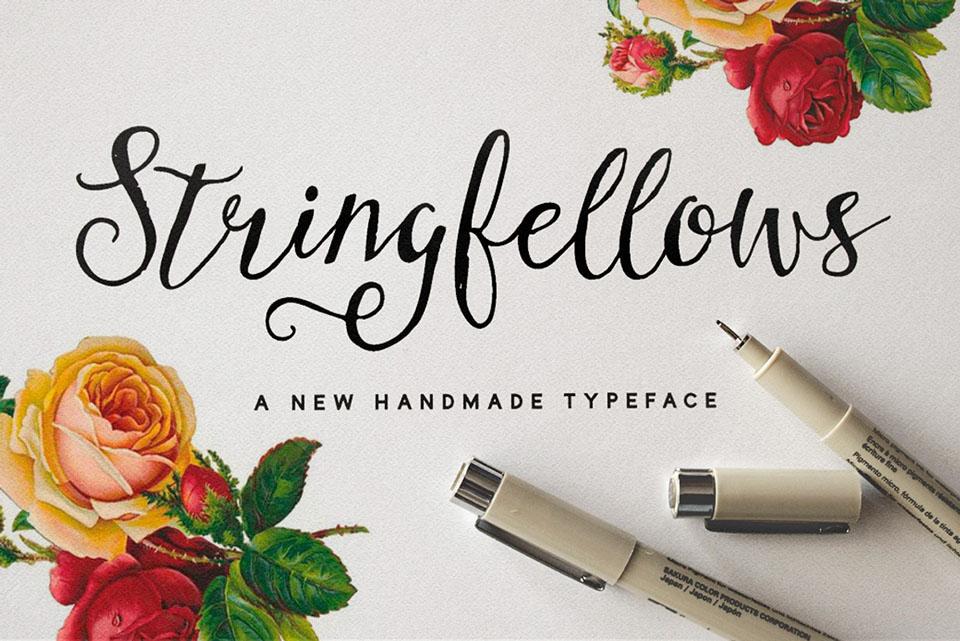
Phân loại: Cá tính
Kiểu chữ: Script
Font iCiel Stringfellows là một kiểu chữ thuộc bộ font iCiel mang sự độc đáo mang phong cách cổ điển kết hợp hiện đại, tạo nên sự cá tính và phá cách trong thiết kế. Với những đường nét thanh thoát, mượt mà và hơi uốn lượn, font này thích hợp cho nhiều dự án sáng tạo như poster, logo, thiệp mời hay bìa sách. Font iCiel Stringfellows không chỉ giúp tạo điểm nhấn đặc biệt mà còn mang lại cảm giác sang trọng, tinh tế cho thiết kế của bạn. Nếu bạn đang tìm kiếm một font chữ có phong cách nghệ thuật và lôi cuốn, font iCiel Stringfellows chắc chắn là lựa chọn lý tưởng.